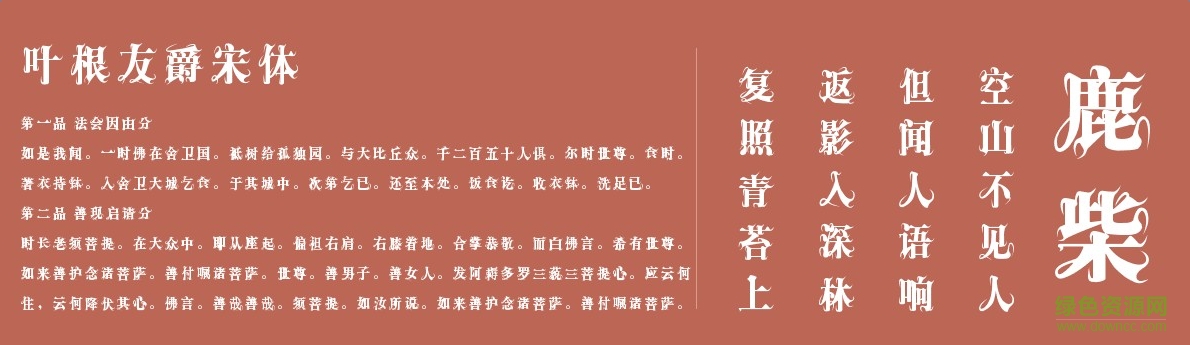
軟件介紹 軟件標簽: 葉根友字體 字體 葉根友爵宋體字體是由中國書法奇人,五筆同書世界首創(chuàng)者,連筆空心字吉尼斯世界紀錄保持者葉根友先生親自書寫的一款字體,是葉根友先生平時書寫最多的一種,也是最為實用的風(fēng)格。字體大方,流暢。歡迎下載!字體安裝方法方法一:控制面板/字體/文件/安裝新字體;方法二:直接將字體復(fù)制到C:\WINDOWS\Fonts。方法三:針對win7系統(tǒng),用戶只需選中字體右鍵安裝即可。注意事項本站所有字體資源僅供個人學(xué)習(xí)與參考,如需商業(yè)使用請到相關(guān)官網(wǎng)授權(quán)。 軟件截圖 上一張下一張(1 / 1) 安裝詳細截圖 猜你喜歡 宋體字體 葉根友 宋體字體 宋體是目前最常用的一款漢字字體,宋體成型于明朝,歷史悠久,字體特點是橫細豎粗,線條平直,結(jié)構(gòu)嚴謹,工整又不失大氣,非常適用于文字排版方面! 查看更多>> 原版宋體 5.37M/中文/1.4/下載 繁體宋體字體打包 14.64M/中文/2.5/免費版下載 經(jīng)典中宋繁 regular 3.26M/中文/5.0/下載 粗標宋體 2.44M/中文/5.0/下載 方太夢想宋字體(中/細/粗體) 6.36M/中文/2.5/非商用下載 宋體-亮體(chinese-gb2312) 5.85M/中文/5.0/下載 葉根友 葉根友字體是現(xiàn)代社會中使用最為廣泛的字體,包含葉根友疾風(fēng)草書、葉根友刀鋒黑草等,現(xiàn)綠色資源網(wǎng)小編整合幾款葉根友字體大全供用戶下載,歡迎到綠色資源網(wǎng)體驗! 查看更多>> 葉根友哲在手寫字體 4.00M/中文/6.0/官方版下載 葉根友離賢行書字體 10.00M/中文/5.7/免費版下載 南構(gòu)字體合集 50.00M/中文/3.7/共16款下載 南構(gòu)汪本友行書字體 10.00M/中文/3.3/下載 南構(gòu)標羽歌士體 10.00M/中文/5.0/免費版下載 南構(gòu)王天喜行書簡體字體 10.00M/中文/2.1/下載 其他版本下載 標題 大小 更新日期 下載 下載地址 電腦版 葉根友爵宋體常規(guī) 點擊報錯 軟件無法下載或下載后無法使用,請點擊報錯,謝謝! 關(guān)閉報錯反饋 請描述您所遇到的錯誤,我們將盡快予以修正,謝謝! *必填項,請輸入內(nèi)容 本類最新 葉根友字體庫打包 共18款 葉根友風(fēng)帆特色簡體 免費官方版 葉根友哲在手寫字體 官方版 南構(gòu)村花手寫體ttf版 南構(gòu)王小花手寫ttf常規(guī) 南構(gòu)日漫風(fēng)字體 相關(guān)文章 Photoshop字體安裝使用方法和技巧 如何解決“無法新增字體”問題 Win 7系統(tǒng)安裝字體方法 網(wǎng)頁字體大小設(shè)置方法 怎么改網(wǎng)頁字體大小 在Linux系統(tǒng)中安裝字體的幾種方法 windows7字體顯示問題:打開某些程序的時候顯示的是亂碼 用戶評論 熱門評論 最新評論 發(fā)表評論 查看所有評論(0) 昵稱: 請不要評論無意義或臟話,我們所有評論會有人工審核. 字數(shù): 0/500 (您的評論需要經(jīng)過審核才能顯示)